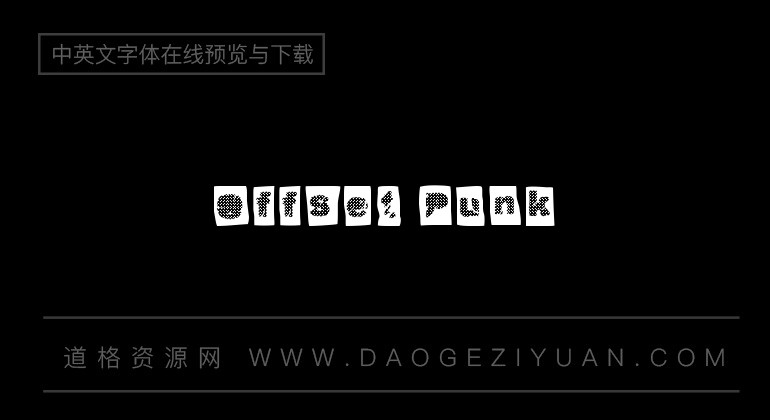
Offset Punk 是一种英文字体,其特点是字母具有偏移和扭曲的效果,看起来具有一定的叛逆和个性化。它的设计灵感来自于朋克摇滚和印刷艺术,因此它的字母看起来就像是从印刷机上刚刚印出来的一样。 Offset Punk 字体的字母形状不规则,有一些字母在左侧或右侧会有一些额外的线条或是错位的效果,这种风格看起来很有视觉冲击力。它的字母间距也比较紧凑,让整个字体看起来更加紧凑和有力量。 Offset Punk 字体适用于一些富有冲击力和个性化的设计项目,比如摇滚音乐海报、街头时尚品牌的标志等等。它的字母看起来很有力量,可以让设计项目更加突出和引人注目。内容介绍
Offset Punk是一款非常不错的手写艺术字体,具有很好的视觉感,适合于文化类的宣传设计、商业类品牌的广告和产品包装设计以及个性化文字排版等较多场景。